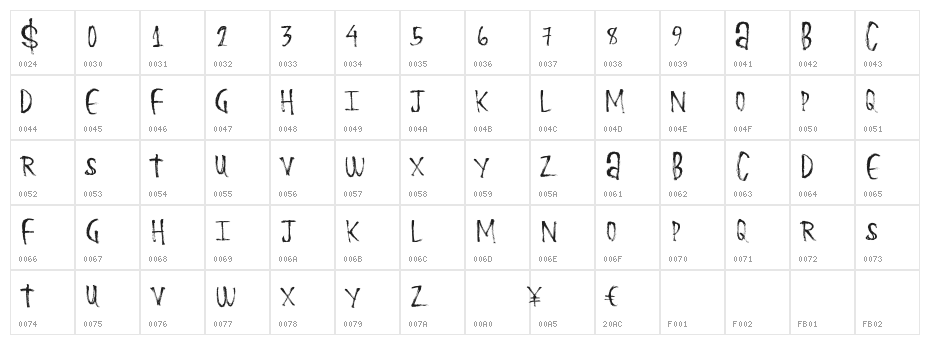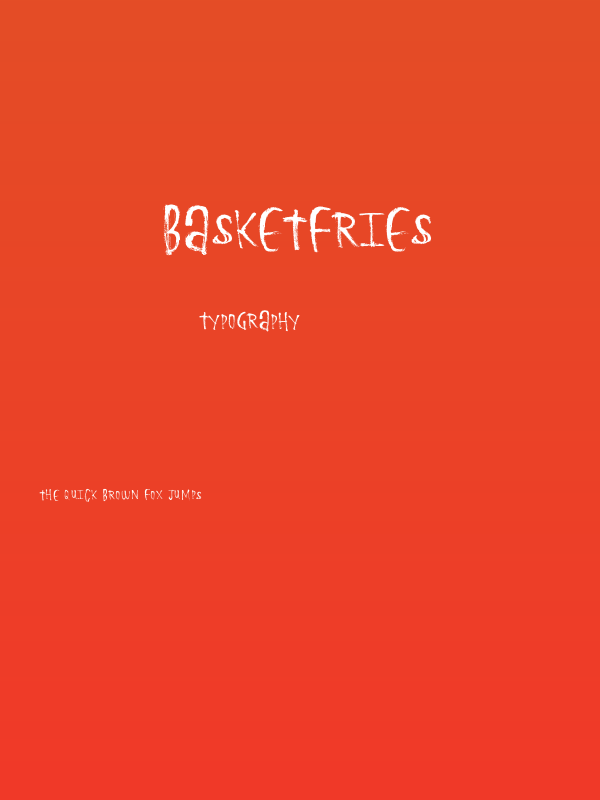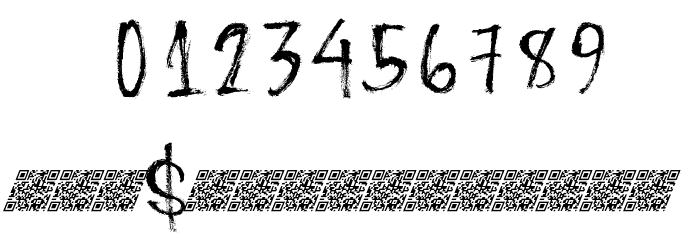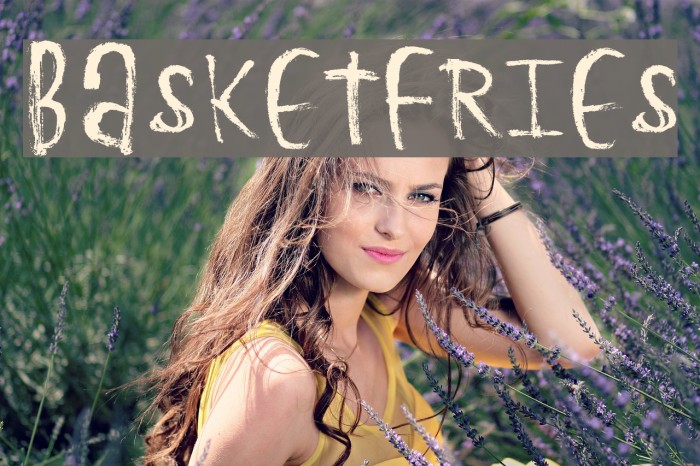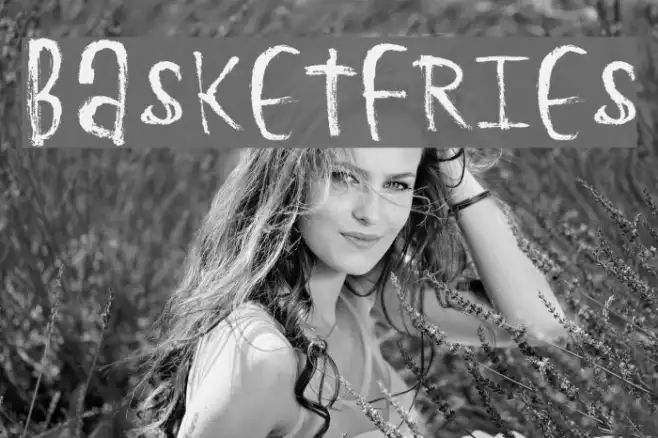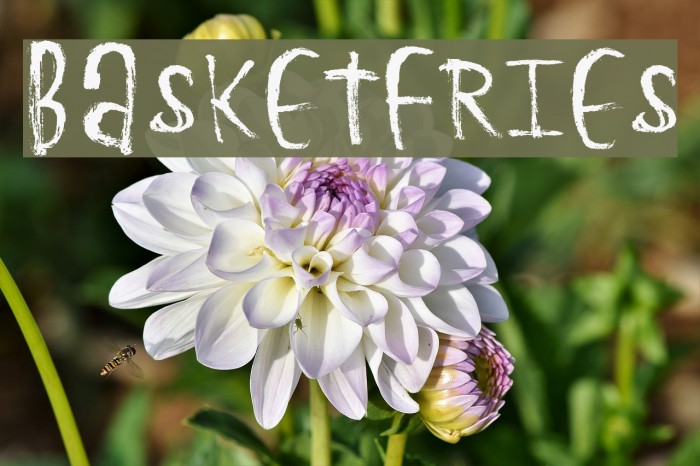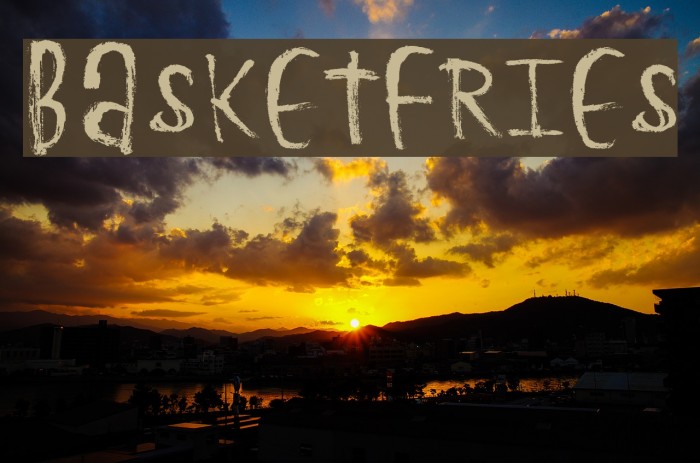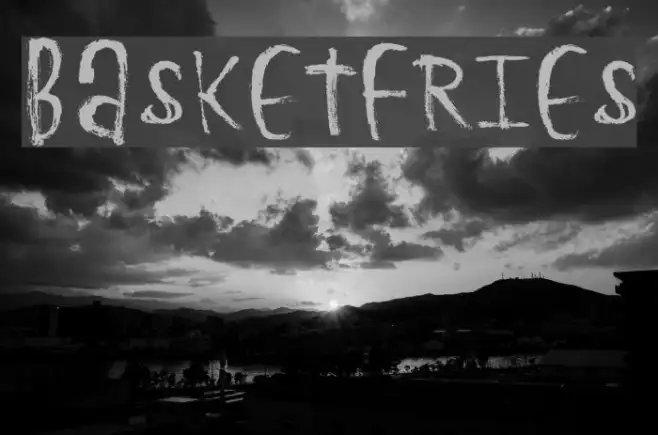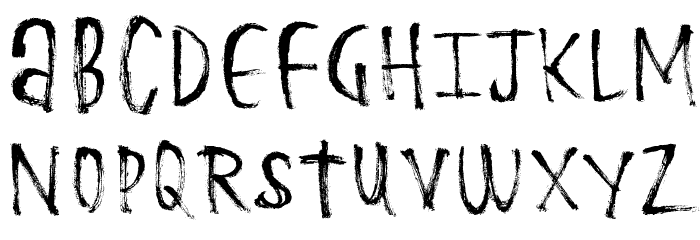
BasketFries Font
✎ Messy
| Proyectos propuestos | Ideal for artistic projects, posters, branding, and any design requiring a creative and informal touch. |